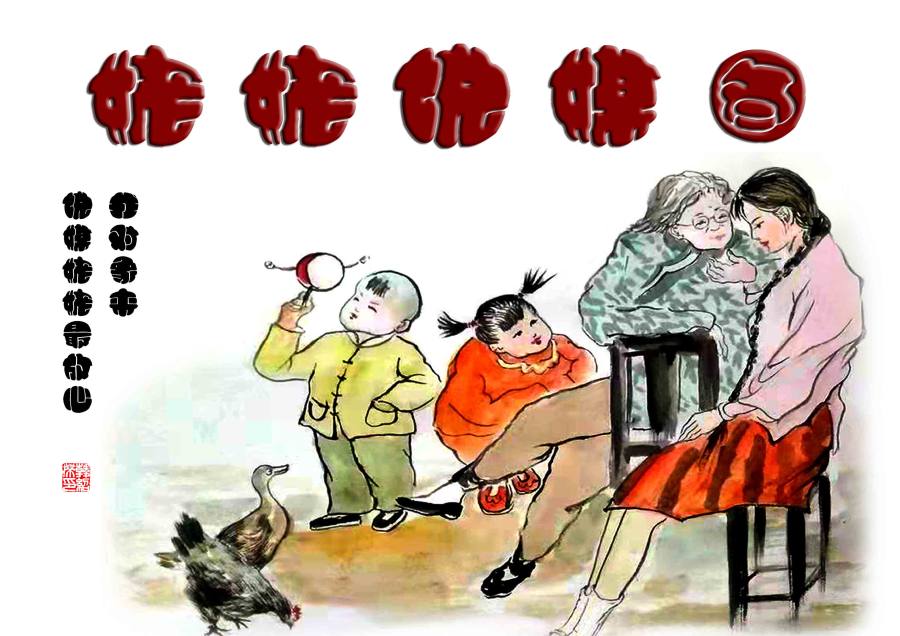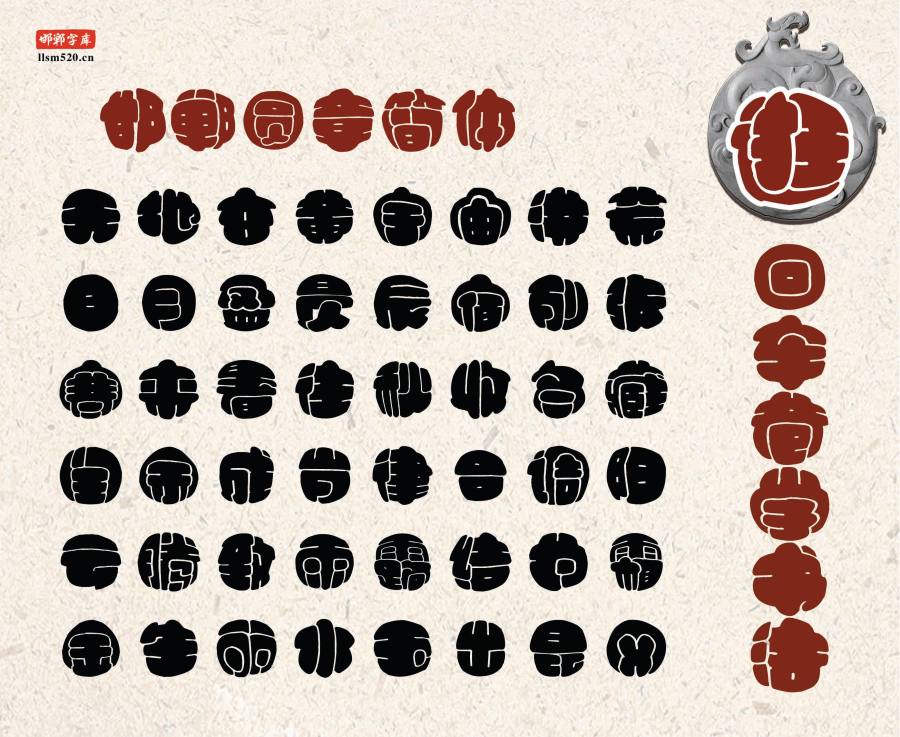
邯郸圆章简体以韩绍杰老师创作的电脑美术字制作而成。该字体笔画粗壮,两端呈圆头,笔画相交紧密,呈凹陷窝状,中宫比较紧凑。黑字面大,字型粗旷,结构严谨,重心一致;外形呈圆形,似篆刻圆章效果,笔划制作精良,线条刚柔相济,简洁有力。阅读舒适流畅,适用于报刊、杂志和书籍中的大型标题。
邯郸圆章简体,笔画粗状、横竖清晰、突出醒目等特点, 外形呈圆形,似篆刻圆章效果,有着非常强烈的艺术感。